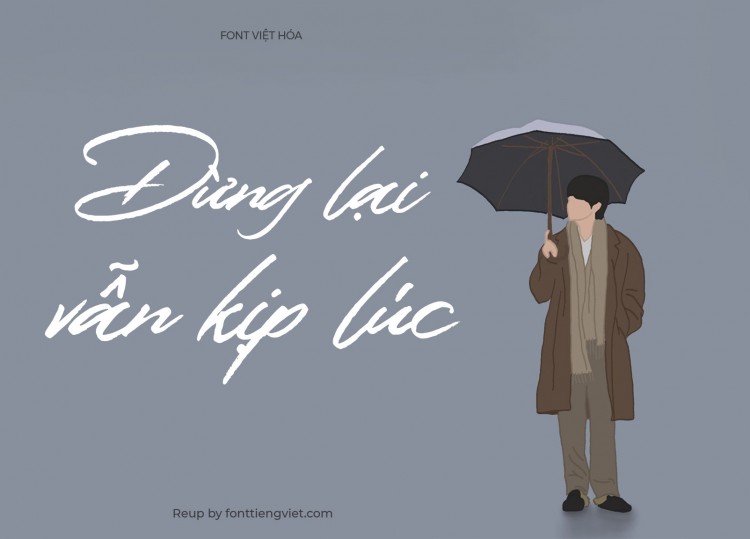
Giới thiệu về bộ Font việt hóa MTD Colatin
Trong thế giới đồ họa, việc lựa chọn một Font Chữ phù hợp đóng vai trò quyết định đến tính thẩm mỹ của sản phẩm. Font việt hóa MTD Colatin là một trong những bộ phông chữ script mang phong cách viết tay mềm mại, uyển chuyển đang được cộng đồng designer Việt Nam săn đón. Với đường nét thanh mảnh nhưng vẫn giữ được sự chắc chắn, bộ font này giúp các bản thiết kế trở nên tinh tế và gần gũi hơn bao giờ hết.
Đặc điểm nổi bật của MTD Colatin
Được chuyển ngữ và tối ưu hóa cho tiếng Việt, bộ font này khắc phục hoàn toàn lỗi dấu bị nhảy hoặc lệch vị trí thường gặp ở các phiên bản gốc. Font việt hóa MTD Colatin sở hữu hệ thống glyph phong phú, cho phép người dùng tự do sáng tạo với các ký tự thay thế đầy nghệ thuật. Đây là lựa chọn hoàn hảo cho các dự án thiết kế thiệp mời, bìa sách, hay các ấn phẩm truyền thông học đường cần sự nhẹ nhàng và thanh lịch.
Ứng dụng thực tế của Font việt hóa MTD Colatin
Nhờ tính ứng dụng cao, font chữ này thường xuyên xuất hiện trong các bộ nhận diện thương hiệu thời trang hoặc mỹ phẩm. Đối với các bạn học sinh và giáo viên, việc sử dụng phông chữ này trong các bài trình chiếu PowerPoint sẽ tạo điểm nhấn thị giác mạnh mẽ, giúp bài giảng trở nên sinh động và thu hút hơn. Sự kết hợp giữa nét cổ điển và hiện đại giúp nó dễ dàng phối hợp với nhiều phong cách thiết kế khác nhau.
Kết luận về bộ font chữ đẹp